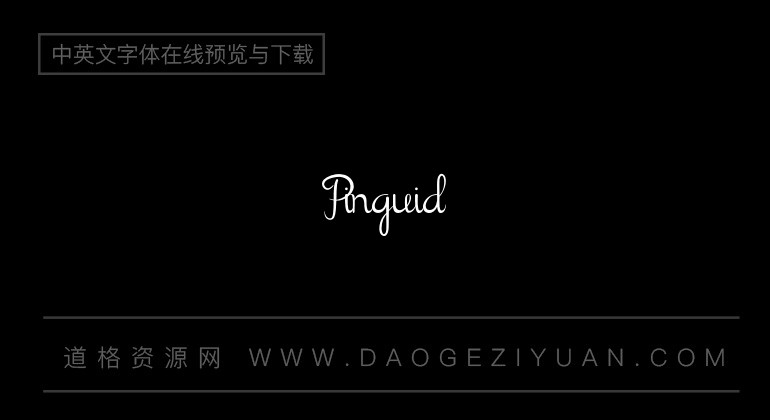
Pinguid
Pinguid 是一种非常流行的手写风格字体。它的特点是字母间距离较小,让文字看起来更加紧凑和有节奏感。此外,Pinguid 字体的字母形状也比较特别,有些字母的笔画比较粗,有些字母的笔画则比较细,整体上给人一种随性和自由的感觉。Pinguid 字体适合用于卡片、海报、标志、包装、标题等设计领域。
Pinguid是一款非常不错的手写艺术字体,具有很好的视觉感,适合于文化类的宣传设计、商业类品牌的广告和产品包装设计以及个性化文字排版等较多场景。